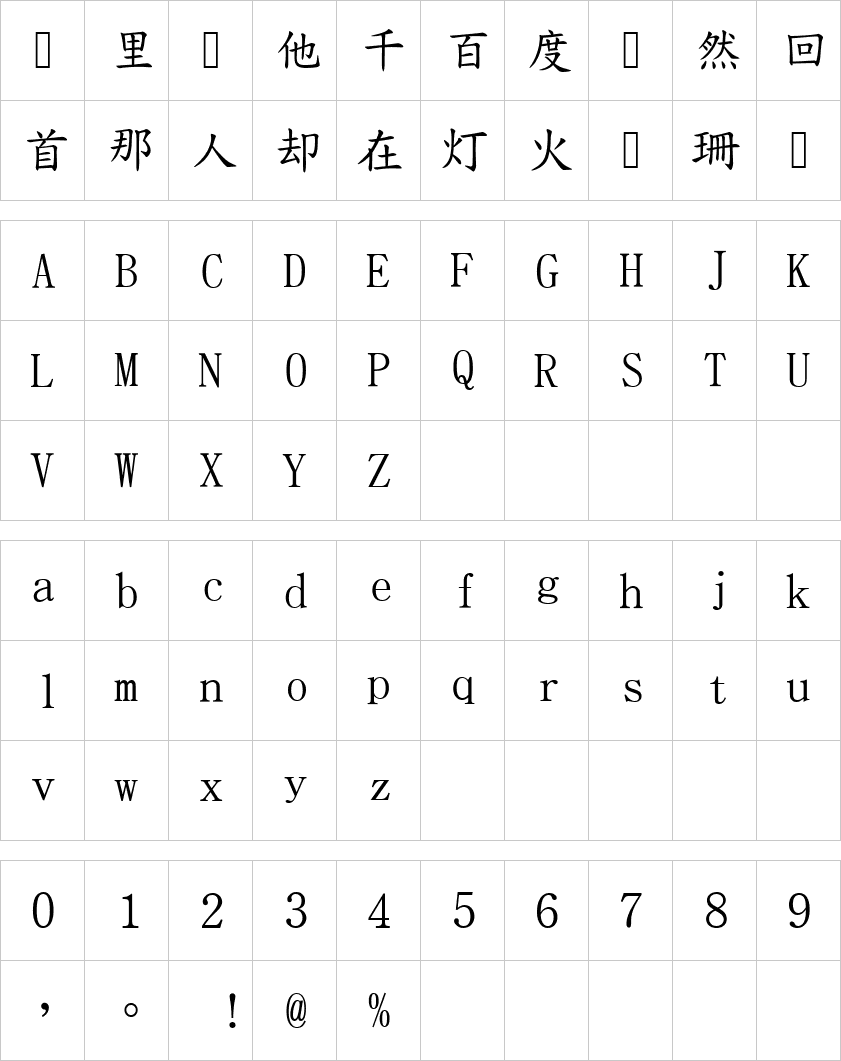
TKaisho-GT01
T字体是由东京大学大学院情报学环·学际情报学府坂村·越冢研究室的跨学科信息研究研究生院维护的大型汉字字体。它由3种TrueType字体,由明朝体、黑体和楷书组成,用于120,000个汉字字符集。120,000个字符的汉字集包括列入“Daikan-WA辞典”(由Daishukan书店出版)由良治诸桥和“康熙字典”字,名称和地名清朝中国。的康熙皇帝编译GT字符大约80,000个字符集,包括汉字,其中包括基于中国宋明时代文学作品中提取的宋明变体字符集大约35,000个字符,以及经典中使用的中国青铜铭文。包括从句子中提取的字符。
结果,我们朝着缺乏汉字字体的问题迈出了一大步,这一直是东亚地区文档信息处理中关注的问题,而在现代日本,每天使用的所谓变体字符问题就是这是一个非常罕见的例外,它不仅几乎可以解决,而且还是可以承受中文书籍(中国古典文学)数字化的字符集,并且是支持东方文化研究的学术基础。